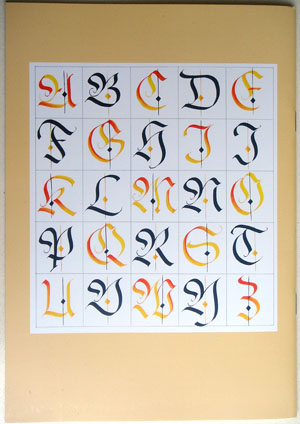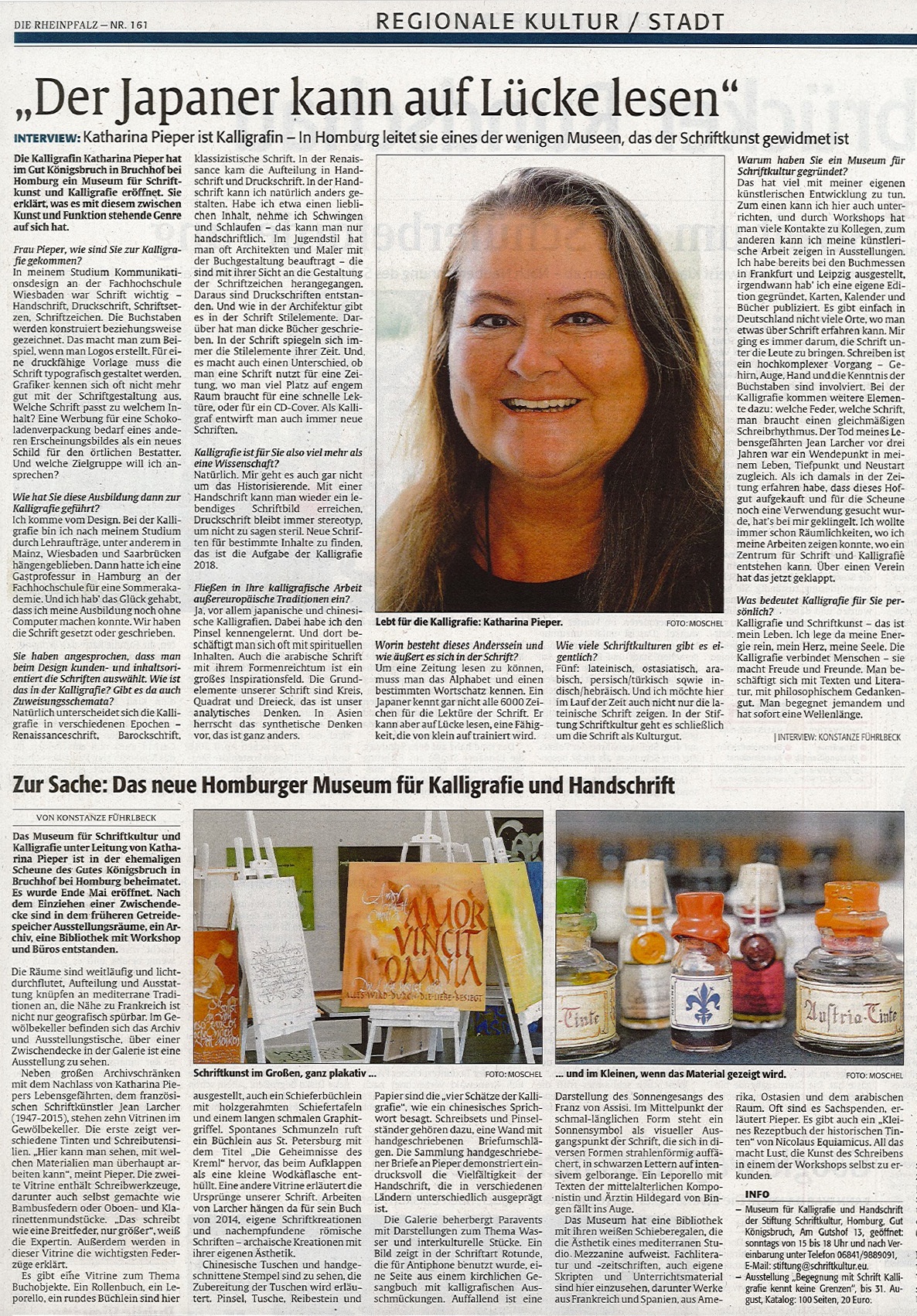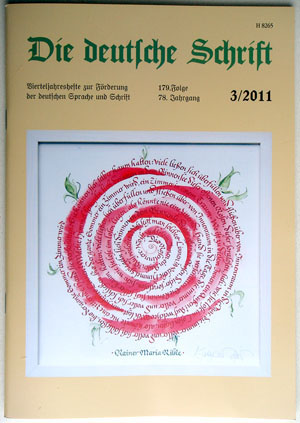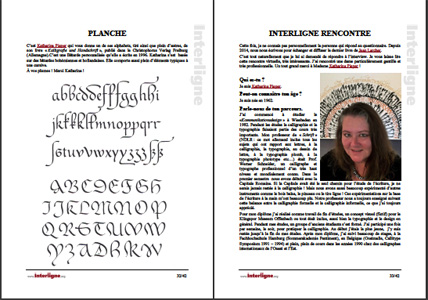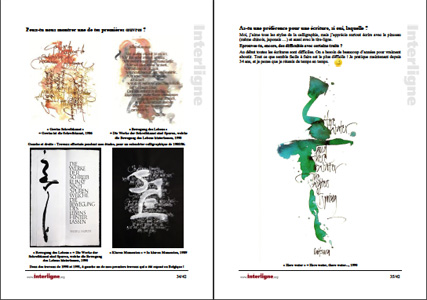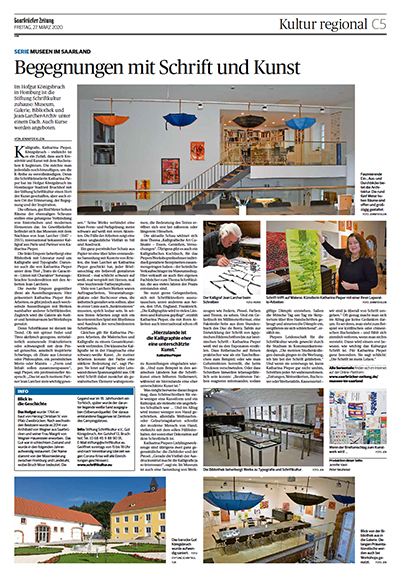
INTERVIEWS MIT KATHARINA PIEPER
Interview von Harald Süß für "Die deutsche Schrift",
Vierteljahresschrift zur Förderung der deutschen Schrift und Sprache,
3/2011, 179. Folge, 78. Jahrgang
Titel und Rückseite der Zeitschrift
Interview von David Heppner für die Seite hobbymap.de
"Es ist das Handgemachte, das im Gegensatz zur Stereotypie des Computerschriftbilds
Tradition und Ursprünglichkeit versinnbildlicht."
Wie Sie alle wissen, ist die Kalligrafie natürlich nicht mein "Hobby" sondern mein Beruf, meine Passion...
Saarbrücker Zeitung vom 13. Februar 2009
Artikel
über Katharina Pieper als Schriftkünstlerin und Dozentin
für Schrift
anlässlich des 125-jährigen Jubiläums des Füllfederhalters
Am
18. August 2008 besuchte die Kunsthistorikerin Verena Paul
Katharina in ihrem Atelier. Es wurde ein interessantes, langes und
gegenseitig befruchtendes Gespräch. Das komplette Interview
können Sie im "Portal Kunstgeschichte"
nachlesen:
Interview von Verena Paul mit Katharina Pieper
Interview mit CaligrafiAR (Buenos Aires - Argentinien)
Die argentinische Kalligrafie-Gesellschaft CalligrafiAr befragte Katharina 2006 über ihre Ausbildung,
ihre Lehrerfahrung und den persönlichen Blickwinkel ihrer künstlerischen Arbeit.
Juli/july 2006 (Englisch/Spanisch) - english/spanish
by Silvina Viola
Interview
für das Dresdener Universitätsjournal am 15.5.2007, 18. Jg., Nr
anlässlich der Ausstellung "Texturen des Herzens" im Herzzentrum
Dresden
Das Interview führte Dagmar Möbius/Dresden
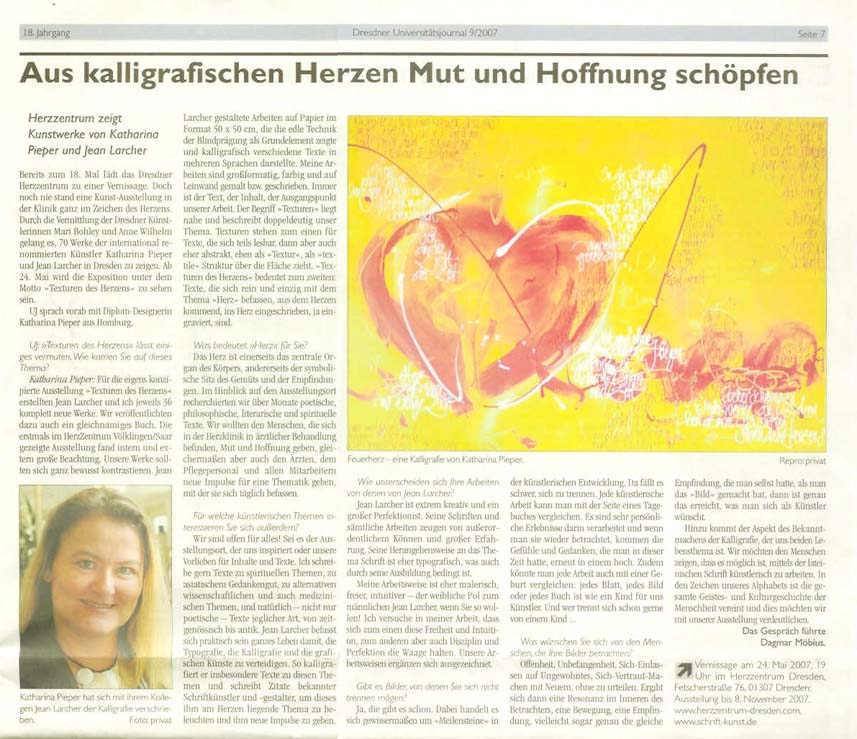
| Interview
für den Berchtesgadener Anzeiger, 28./30. September 2001: ________________________________________________________________ 1) Wie kamen Sie zu Ihrem Metier? Was hat Sie an der Schrift als Berufsaufgabe gereizt? K.P.: Durch mein Studium "Kommunikationsdesign" in Wiesbaden habe ich Professor Werner Schneider kennengelernt. Seine Kompetenz und sein Enthusiasmus waren mein Einstieg in die "Faszination Schrift". Direkt nach meinem Studium folgten Lehraufträge für Schrift an den Fachhochschulen Mainz und Saarbrücken. So ergab sich der weitere Lebensweg. Während meiner inzwischen fast 20jährigen Berufserfahrung musste ich viele Tiefschläge und Veränderungen einstecken. Das Medium Computer hat die Welt des Grafik Design während dieser Zeit komplett verwandelt. 2) Was ist das Faszinierende am langsamen Medium Handschrift oder gar Kalligraphie? K.P.: So langsam muss das gar nicht sein! Alles ist relativ! Man kann sehr expressiv und schnell eine Zeichenfolge aufs Papier setzen. Und hier ist es, wie so oft: das schwere ist das scheinbar leichte! Das, was wie hingeschwebt aussieht, ist am allerschwierigsten! Viele Jahre konzentrierten Übens sind hier vonnöten, um eine exzellente Qualität zu erhalten. Die historischen Schriftformen können natürlich nicht so schnell geschrieben werden, da haben Sie schon recht. Hier bedarf es Zeit und Ruhe, und oft dauert es sogar länger, bis die Linien gezogen oder die Textmenge ausgerechnet ist als das Schreiben selbst. Doch es fasziniert mich, da§ man mit ausdrucksvoll gestalteter Schrift ganz wunderbar und adäquat Inhalte sichtbar machen kann. Und: ein Betrachter kann es sogar noch lesen und damit erfassen. Doch auch hier gilt wieder: schon die äußere Form kann auf den Inhalt hinweisen, so da§ es sich sogar erübrigen kann, das Geschriebene zu lesen. Semantische Schriftgestaltung nennen wir dies. Hier steht die Lesbarkeit nicht an erster Stelle. Mittels Schrift, Zeichen, Alphabet können Gefühle und Gedanken sichtbar gemacht werden. All unsere Kultur steckt in den Zeichen des Alphabets. 3) Worin unterscheidet sich eine schöne Handschrift von perfekter Maschinen- oder Computerschrift - abgesehen von der Funktionalität? K.P.: Eine (schöne) Handschrift ist immer individuell und ganz persönlich. Gedanken und Gefühle können sichtbar gemacht werden. Das macht die Schrift menschlich. Der Mensch ist nicht perfekt, und so kann eine handgeschriebene Schrift auch nicht "perfekt" sein. Der Computer täuscht Perfektion vor. Das macht die Computerschrift steril und unmenschlich. Damit möchte ich nicht sagen, daß es nicht auch ausgezeichnete Computerschriften gibt. Doch diese müssen unbedingt von Fachleuten geschaffen werden und nicht von solchen, die sich dafür halten. 4) Computer "erleichtern" uns immer mehr das Arbeitsleben. Bald sprechen wir mit den GerŠten, und es erscheint dann ein schriftlicher Text. Wohin entwickelt sich Ihrer Meinung nach unsere Schreibkultur? K.P.: Das stimmt, die technische Entwicklung geht so rasant vonstatten, da§ wir nur noch staunen können. Die Handschrift besitzt in den Schulen einen immer geringeren Stellenwert. Selbst die Lehrenden können oft nicht mehr gut, geschweige denn schön schreiben. Das ist ein Problem. Es wird immer Menschen geben, die sich mit der Handschrift auseinandersetzen, doch, wie es aussieht, eher im Sinne eines Hobbys. Gestaltete Schrift in der Werbung oder Informationsgrafik ist heute notwendiger denn je. Hier mu§ vor allem die Ausbildung für Designer wieder besser werden. 5) Gibt es Materialien, die Sie bei Ihrer Arbeit besonders bevorzugen? (Papiere, Stifte) Wieso? K.P.: Ja. Ich schreibe z.B. besonders gerne mit einem (chinesischen oder japanischen) Pinsel. Seine lebendige Flexibilität beseelt die Bewegungen auf dem Papier. Auch die Ziehfeder, die man früher zum technischen Zeichnen benutzt hat, ist eines meiner Lieblingswerkzeuge. Hier entstehen expressive Schriftzüge von höchster Eleganz. Ich lasse mir von Spezialisten gerne Federn speziell für meine Hand anfertigen, oder ich mache sie selbst. Eine Bambusfeder, ein Balsa Holz oder ein Furnier kann man selbst gut und billig herstellen. Zu den Papieren mu§ ich sagen, da§ es hier so viele tolle Möglichkeiten gibt. Es kommt ganz darauf an, was man machen möchte. Ein handgeschöpftes Büttenpapier ist hervorragend, doch nicht jede Feder läuft auf jedem Papier. Hier muss man ganz viel experimentieren. 6) Welche Rolle spielen Bleistifte in ihrem kreativen Leben? K.P.: Mit dem Bleistift skizziere ich meistens, ziehe Linien, signiere oder bestimme den Stand von Buchstaben. In meinem Unterricht lasse ich mit Bleistiften unterschiedlicher Härtegrade Schrift skizzieren oder bestimmte Schwünge üben. 7) Wie gehen Printmedien (Zeitungen, Zeitschriften) Ihrer Ansicht nach mit Schrift um? Gibt es gute oder besonders abschreckende Beispiele? K.P.: Es gibt tatsächlich gute, aber noch wesentlich mehr abschreckende Beispiele gestalteter Schrift. Zu viele Leute bedienen sich heute der Schrift, die davon keine Ahnung haben. Hier muss die Ausbildung (s.o.) unbedingt wieder verbessert werden. Sicher gibt es gute Zeitungs- oder Buchtypografie. Das hat aber nichts mehr mit Handschrift, sondern rein mit der Schriftanwendung bestehender Typen zu tun. Doch Schrift kommt ursprünglich immer noch vom Schreiben, wenn dies auch die modernen Typografen heute leugnen wollen. 8)Wer besucht heute noch Kalligrafie-Kurse und mit welchem Ziel? K.P.: Es gibt inzwischen so viele Kurse, die zum Thema Schrift angeboten werden, dass man den Überblick verliert. Leider nennen sich oft Anfänger schon Kalligrafen und geben bereits nach einem VHS-Kurs selbst Kurse. Da bleibt die Qualität natürlich auf der Strecke. Ich selbst gebe viele Kurse, zu denen ich als Referentin eingeladen werde. Auch auf Symposien, die weltweit organisiert werden (z.B. in England, USA oder Belgien). Hierher kommen vom ausgebildeten Designer über künstlerisch Tätige, Lehrer, Bibliothekare, Psychologen, sogar Pfarrer oder Ärzte bis hin zu Schülern, Studenten, Rentnern und Hausfrauen alle Berufs- und Altersklassen. Meine jüngste Kursteilnehmerin war 11, mein ältester Kursteilnehmer 82 Jahre. Die Menschen möchten oft ihre eigene Handschrift verbessern, Lieblingsgedichte schön schreiben oder einfach nur Glückwünsche schreiben können. Sie haben Freude an künstlerischer Gestaltung, dem Umgang mit Feder, Tinte, Papier. Und fast immer ist es auch die Literatur, die Philosophie, Geschichte oder Religion, die die Menschen von jeher fasziniert hat und deren Gedankengut sie mittels gestalteter Schrift ausdrücken und umsetzen können. Das Interview führte Iris Melcher. |